Ketika ingin membuat poster, maka kamu harus memperhatikan beberapa elemen penting di dalamnya. Salah satu elemen penting itu adalah pemilihan font yang tepat.
Karena dengan memakai font yang tepat, desain poster yang akan dibuat juga akan semakin menarik. Namun lebih direkomendasikan lagi memilih font sesuai event di poster tersebut.
Nah lewat artikel ini, kami akan menjelaskan daftar rekomendasi font untuk poster yang bisa kamu download secara gratis.
Daftar Font Untuk Desain Poster
Secara garis besar, poster memiliki banyak fungsi. Mulai dari untuk mempromosikan event hingga penjualan barang atau jasa.
Oleh sebab itu, tidak hanya desainnya saja yang harus diperhatikan dan disesuaikan dengan tujuan poster. Melainkan pemilihan font juga harus dilakukan dengan tepat.
Berikut rekomendasi daftar font untuk desain poster:
- 1. Edge of the Galaxy Font
- 2. Babillon Font
- 3. Atlane Font
- 4. BATIK WORLDWIDE Font
- 5. Ombudsman Alternate
- 6. Hamble Font
- 7. Blindshot Font
- 8. Moonshine Font
- 9. The Brilliant Font
- 10. Millena Font
- 11. Hot Jacket Font
- 12. Boldblaster Font
- 13. Predator Movie Font
- 14. Justice League Font
- 15. Suicide Squad Font
- 16. Shojumaru
- 17. Gravitas One
- 18. Ubuntu Titling
- 19. Ostrich Sans Inline
- 20. Trade Winds
- 21. Hardcore Poster
- 22. Carnage Movie Poster
- 23. Skeleton Type One
- 24. GoGo Poster 2020 Font
- 25. The Poster King
- 26. Gunplay Font Family
- 27. Beyond Wonderland Font
- 28. Pricedown Font
- 29. Alba Font Family
- 30. Casper Font
1. Edge of the Galaxy Font
Font poster yang kami rekomendasikan pertama ialah Edge of the Galaxy. Font yang didesain bertema sci-fi ini sangat cocok dipakai untuk beberapa event di poster.
Misalnya seperti poster untuk event teknologi, film, karya senin dan lainnya. Menariknya, font ini juga menyediakan 4 jenis desain yang bisa kamu pakai.
2. Babillon Font
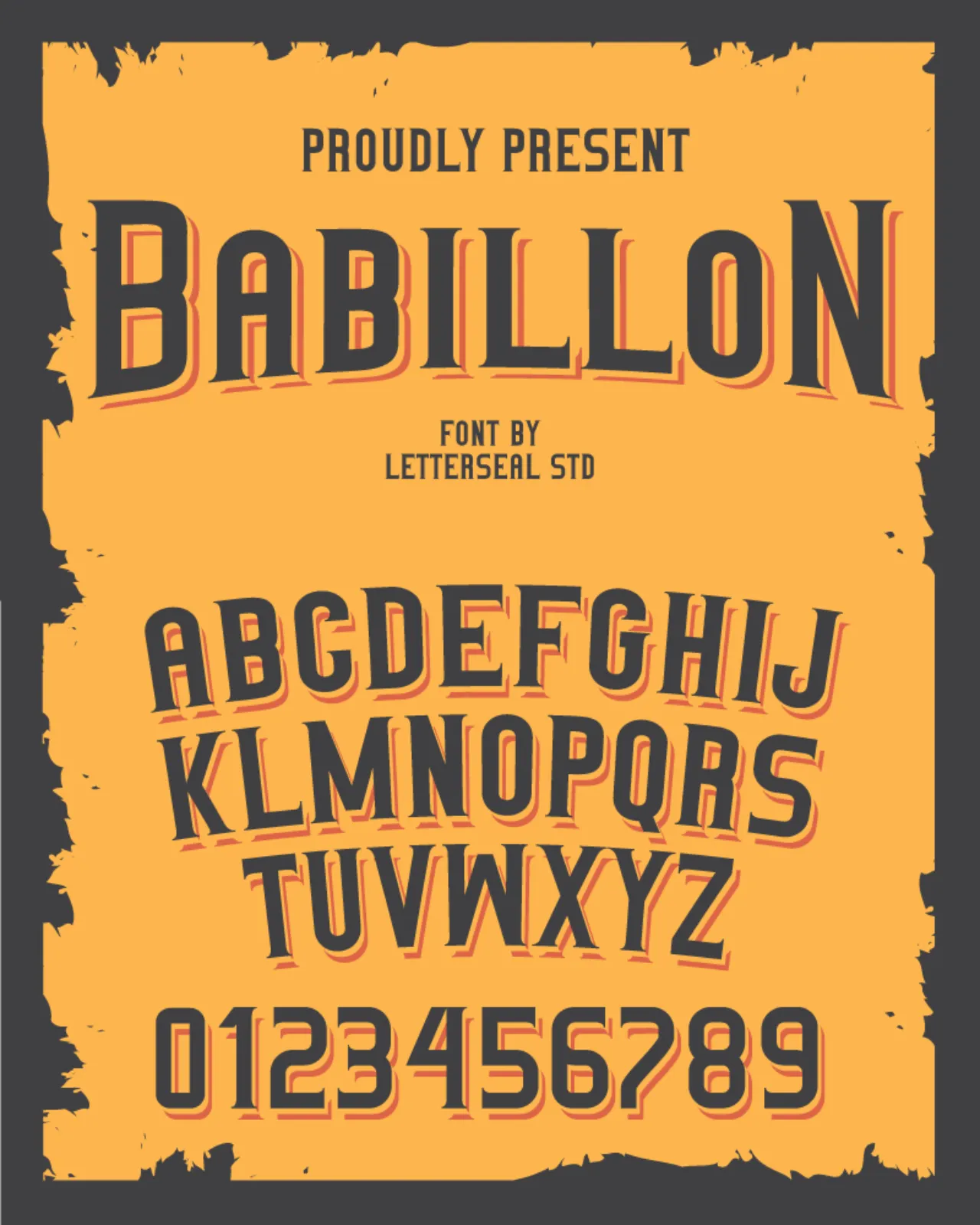
Dari kelompok font serif yang cocok untuk poster ada Babillon. Font yang memiliki desain tebal dan punya sedikit sisi setiap sudutnya membuat font ini terlihat keren.
Terutama untuk poster untuk event tertentu, misalkan seperti musik, acara sekolah, kuliah dan lainnya.
Namun font ini tidak memiliki desain untuk huruf kecil, melainkan huruf besar dan angka saja.
3. Atlane Font
Kemudian untuk poster event karya seni rupa, Atlane font bisa menjadi pilihan kamu. Alasannya karena font ini memiliki coretan di beberapa karakter sehingga terlihat aesthetic.
Selain untuk membuat poster, font ini juga cocok dipakai untuk membuat logo ataupun watermark.
4. BATIK WORLDWIDE Font
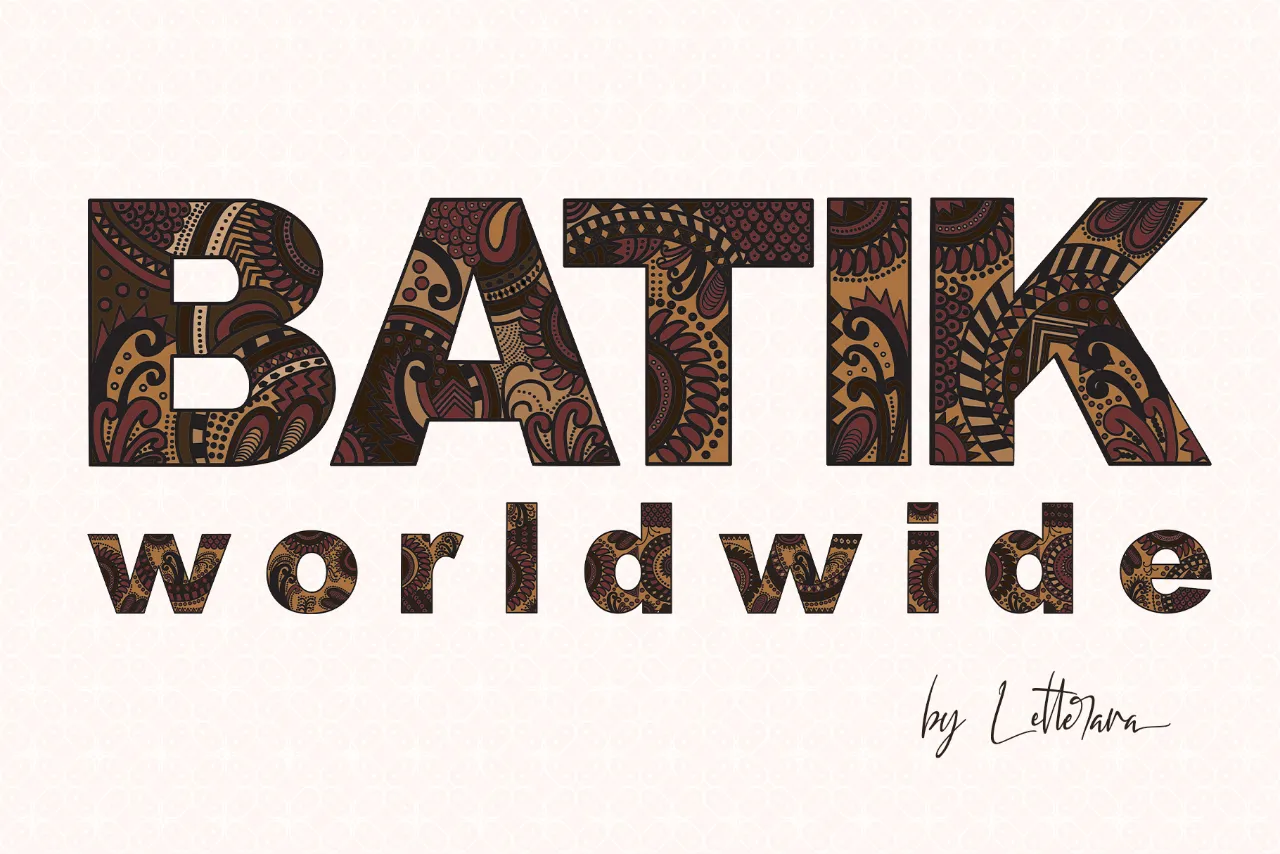
Lanjut lagi ada BATIK WORLDWIDE font yang cocok untuk pembuatan poster bertema Indonesia.
Font asal Indonesia ini didesain khusus dengan fill batik. Sehingga terkesan unik dan kental akan budaya Indonesia.
5. Ombudsman Alternate
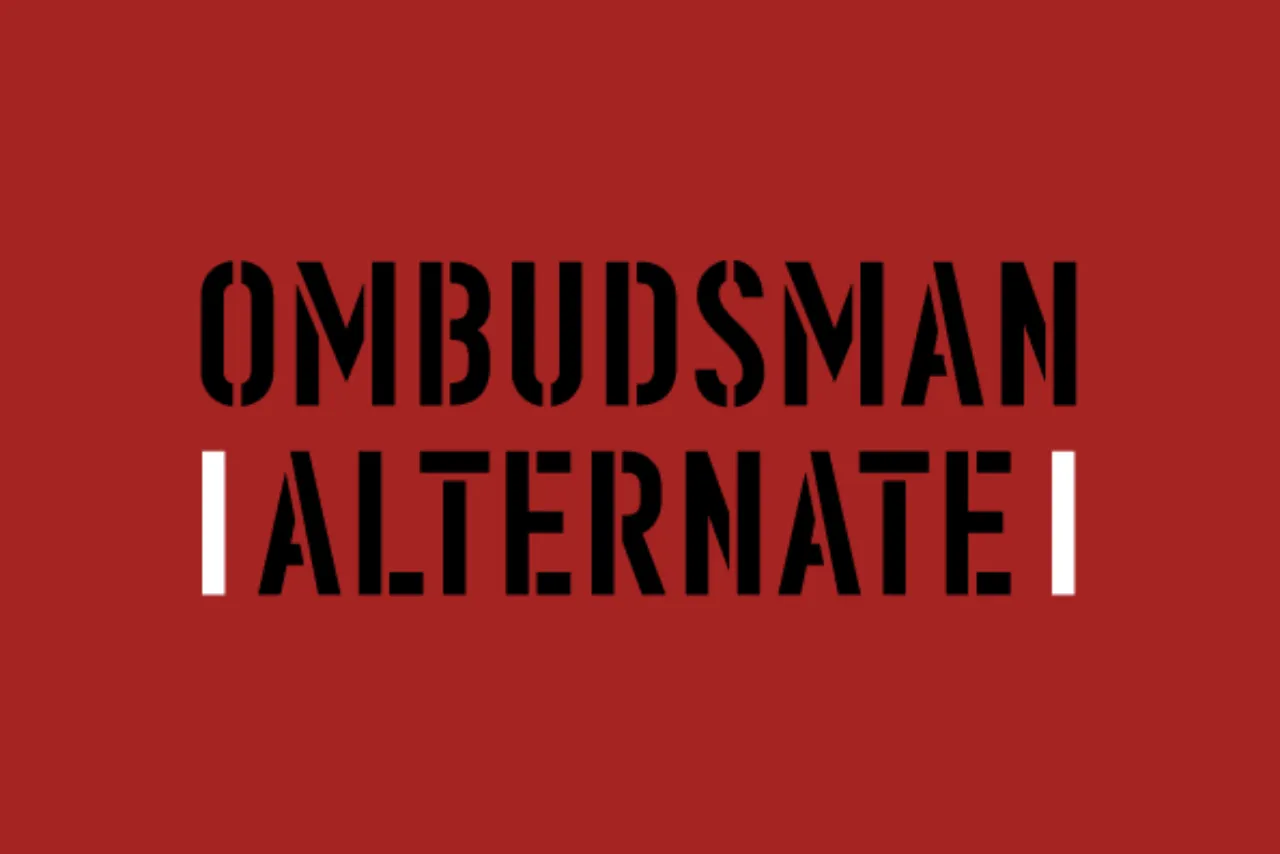
Kalau kamu ingin mencari font poster unik lainnya, kamu bisa pakai Ombudsman Alternate. Font yang memiliki goresan di setiap karakternya ini juga sangat cocok untuk pembuatan poster.
Utamanya poster yang berkaitan dengan jurnalis, hukum dan sejenisnya. Menariknya, font ini terdiri dari 158 karakter yang terdiri dari huruf besar, angka dan simbol khusus.
6. Hamble Font
Kalau kamu mencari font tipografi, Hamble adalah salah satu yang kami rekomendasikan.
Memiliki desain yang bervariasi dan dekoratif di setiap karakter membuat font ini terlihat sangat menarik. Apalagi kalau dipakai untuk event karya seni, class meeting dan lainnya.
7. Blindshot Font
Kemudian untuk font dengan desain brush kamu bisa pakai Blindshot. Font ini memiliki desain yang terkesan liar, sehingga cocok untuk pembuatan poster musik rock atau hardcore.
Selain itu, font ini juga terdiri dari 136 karakter yang terdiri dari simbol khusus, angka dan huruf besar.
8. Moonshine Font
Moonshine adalah salah satu font cursive yang cocok untuk membuat poster. Font dengan desain fill tidak merata ini sangat terlihat menarik.
Karena terdapat juga desain dekoratif yang ada di setiap karakter dari font tersebut. Selain cocok untuk pembuatan font, biasanya Moonshine juga dipakai untuk membuat sablon baju.
9. The Brilliant Font
Dari font kaligrafi ada The Brilliant font. Font yang memiliki kesan ditulis dengan brush dan didesain kaligrafi ini sangat cocok dipilih untuk pembuatan judul poster.
Terutama untuk event poster seperti class meeting, karya seni dan lainnya. Selain itu font ini juga memiliki 353 karakter yang terdiri dari huruf besar, kecil, angka, simbol khusus dan mathematics operator.
10. Millena Font
Adapun Millena font dari desain handwriting dan modern kaligrafi. Font ini juga memiliki sisi keunikan tersendiri, karena terdapat simbol hati di beberapa karakternya.
Karena hal ini, membuat Millena font sangat cocok dipakai untuk membuat poster event feminim. Misalkan seperti poster pelatihan make up, tanaman, karya seni dan lainnya.
11. Hot Jacket Font
Kalau Millena font khusus untuk event poster feminim, maka Hot Jacket ini didesain khusus untuk acara laki-laki. Misalkan seperti musik jass, coffee, kaos distro dan lainnya.
Alasannya karena desain yang ada di font ini memiliki kesan maskulin dengan dekorasi di beberapa karakter.
12. Boldblaster Font
Lalu ada font script Boldblaster yang bisa kamu pakai juga untuk membuat poster. Font ini memakai format bold dan didesain soft supaya terlihat menarik.
Selain itu, font ini juga terbilang memiliki karakter yang sangat lengkap karena terdiri dari 343 karakter. Karakternya seperti huruf besar, huruf kecil, angka, simbol dan karakter khusus.
13. Predator Movie Font
Font Predator Movie. Font ini sangat cocok untuk pembuatan poster film, atau event berkaitan dengan IT.
Dari desain, font ini cocok dipakai untuk membuat judul poster saja. Sedangkan untuk isi poster, kamu harus mencari font yang tipis.
14. Justice League Font
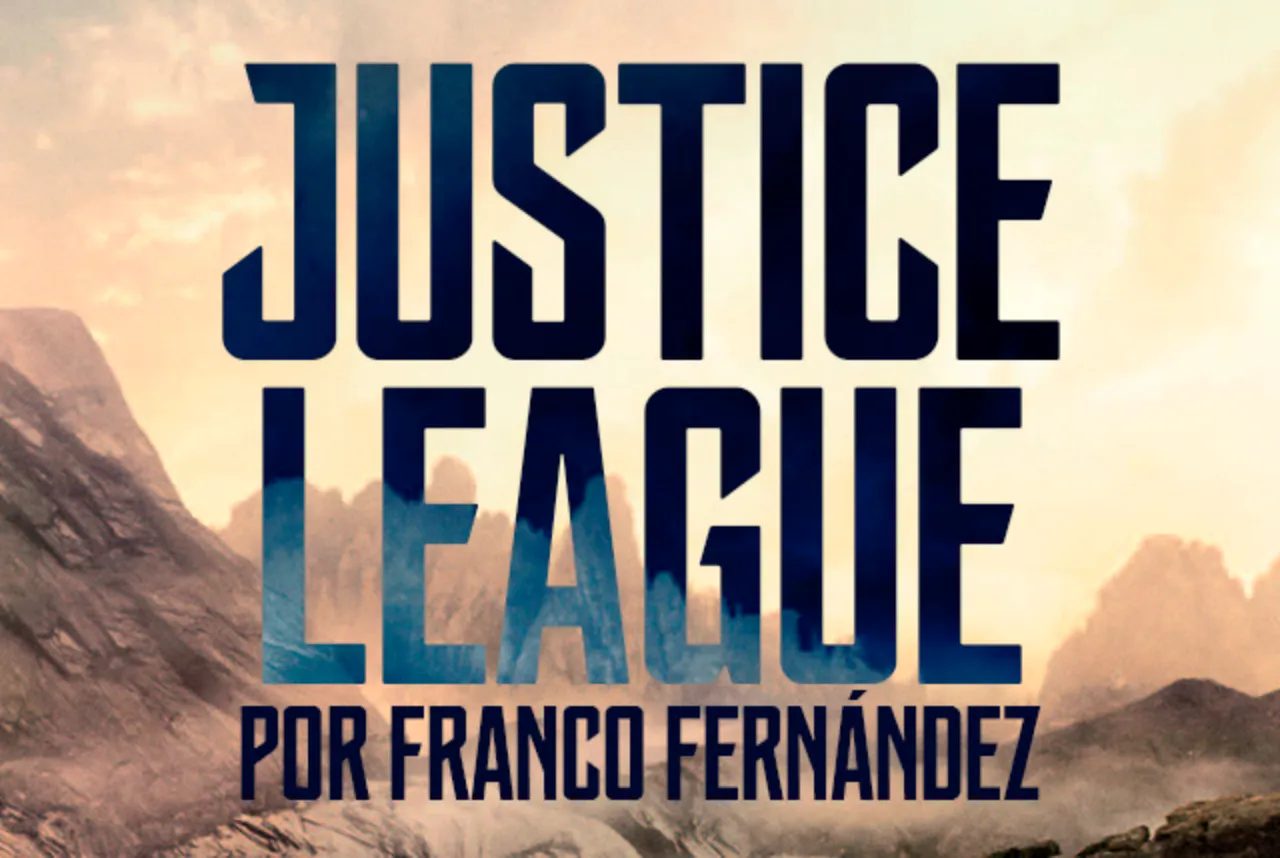
Font ini cocok dan biasa dipakai untuk pembuatan poster film, yaitu Justice League. Biasanya font ini sering digunakan untuk film yang berkaitan dengan superhero.
Selain untuk pembuatan poster film, font ini juga cocok untuk membuat poster yang berkaitan dengan teknologi.
15. Suicide Squad Font
Apa kamu pernah menonton film Suicide Squad? Ya, film yang menggambarkan villain superhero memakai font ini untuk pembuatan poster filmnya.
Oleh karena itu, font ini memiliki sisi keunikan sendiri. Karena terdapat beberapa karakter dengan gambar joker, seperti di huruf A, B, D, O dan lainnya.
16. Shojumaru
Shojumaru adalah salah satu font yang cocok dipakai untuk membuat poster bertemakan jepang.
Alasannya karena font ini sedikit mengambil desain huruf kanji yang dipadukan dengan beberapa sisi unik di setiap karakter.
17. Gravitas One
Kalau kamu ingin memakai font sederhana untuk poster, maka kamu bisa pakai Gravitas One. Font serif modern ini sangat cocok dipakai untuk membuat poster event apapun.
Selain itu, font ini juga terdiri dari 240 glyphs yang terdiri dari huruf besar, kecil, angka dan sebagainya.
18. Ubuntu Titling
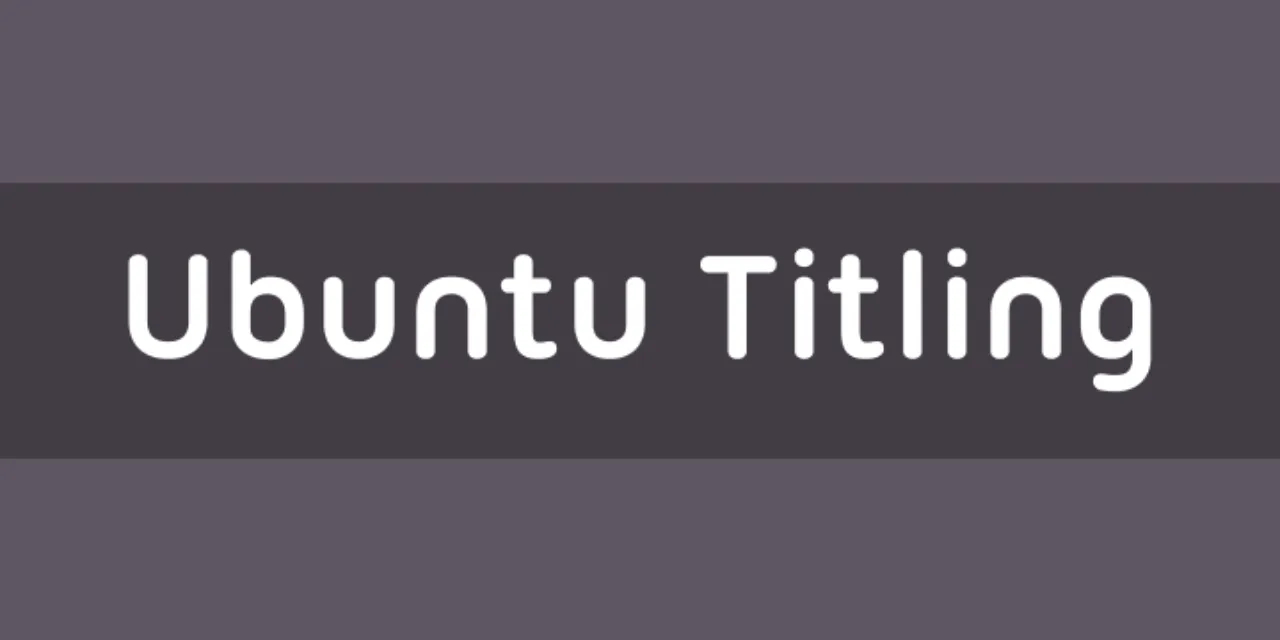
Bagi kamu yang memakai sistem operasi Linux Ubuntu, font ini sangat cocok dipilih. Karena font ini memiliki bentuk layaknya logo Ubuntu itu sendiri.
Karena hal tersebut, membuat font Ubuntu Titling ini cocok dipakai untuk pembuatan poster event teknologi.
19. Ostrich Sans Inline
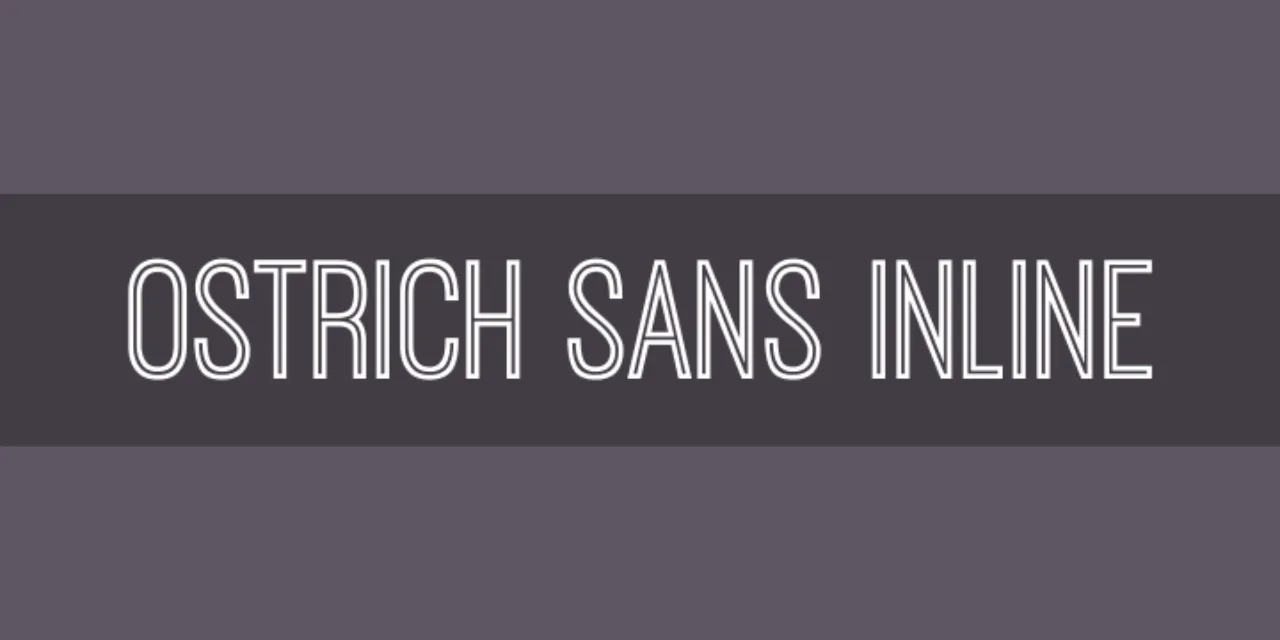
Kemudian kalau kamu ingin memakai font tanpa fill, maka bisa pakai Ostrich Sans Inline. Font ini tersedia 2 jenis, yaitu dengan format regular dan italic.
Menariknya, font ini juga cocok untuk membuat poster event apapun. Karena memiliki desain sederhana, hanya tidak memiliki fill saja.
20. Trade Winds
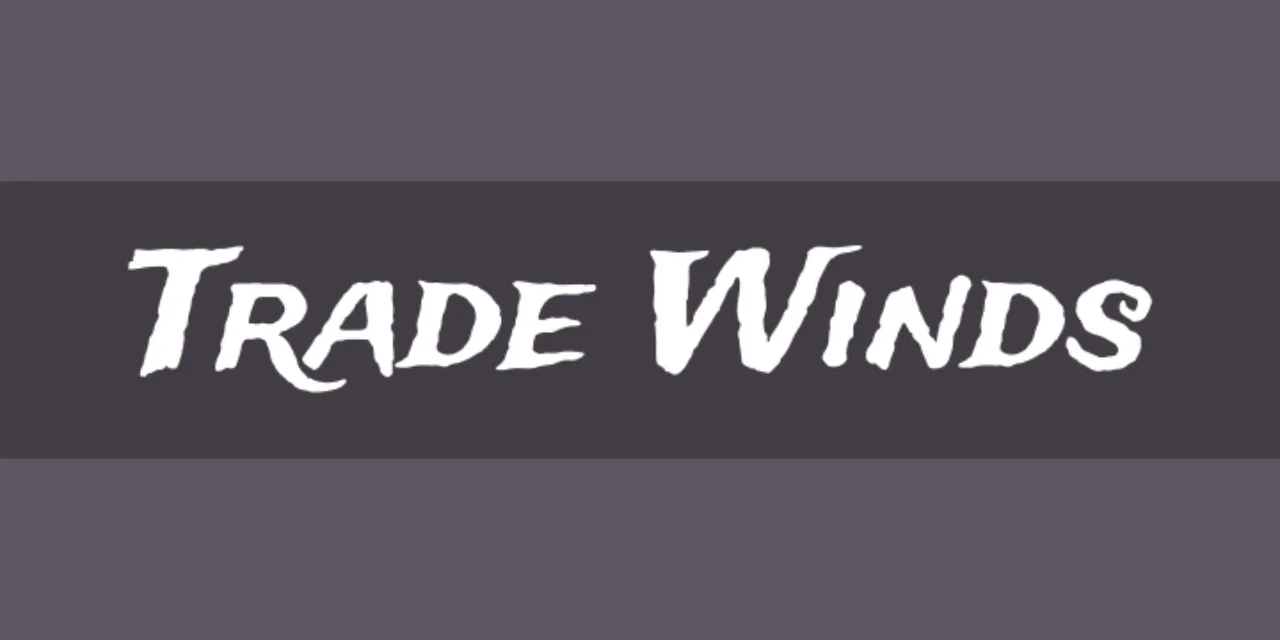
Font yang direkomendasikan untuk membuat poster lainnya adalah Trade Winds. Font dengan desain rough ini sangat cocok dipilih untuk membuat poster tertentu.
Misalkan seperti poster musik, kaos pria dan lainnya. Selain itu, desain di font Trade Winds ini juga cocok dipakai untuk membuat mockup sablon baju.
21. Hardcore Poster
Sedangkan ada Hardcore Poster font yang didesain khusus untuk event musik genre hardcore atau rock.
Biasanya font ini dipakai untuk membuat judul font karena hanya menyediakan karakter huruf besar dan angka saja.
22. Carnage Movie Poster
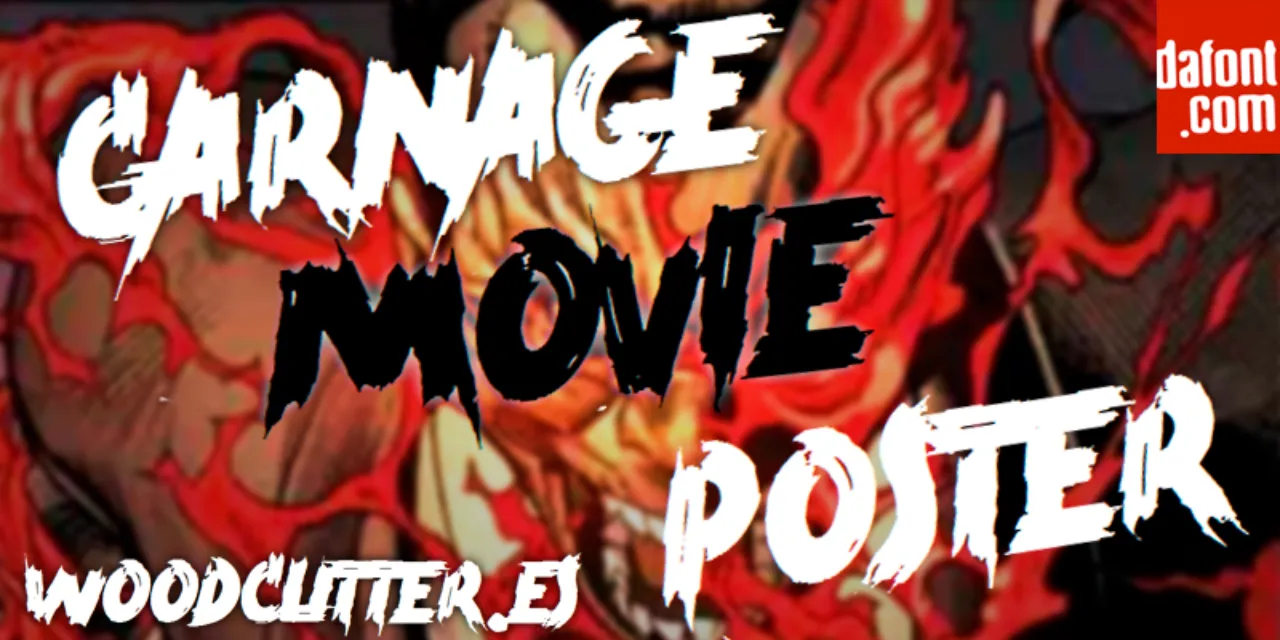
Kalau Carnage Movie Poster bisa kamu pakai untuk membuat poster bertemakan horror. Entah itu film, event rumah hantu atau sebagainya.
Alasannya karena font ini didesain khusus dengan efek brush namun terlihat sedikit keras.
23. Skeleton Type One
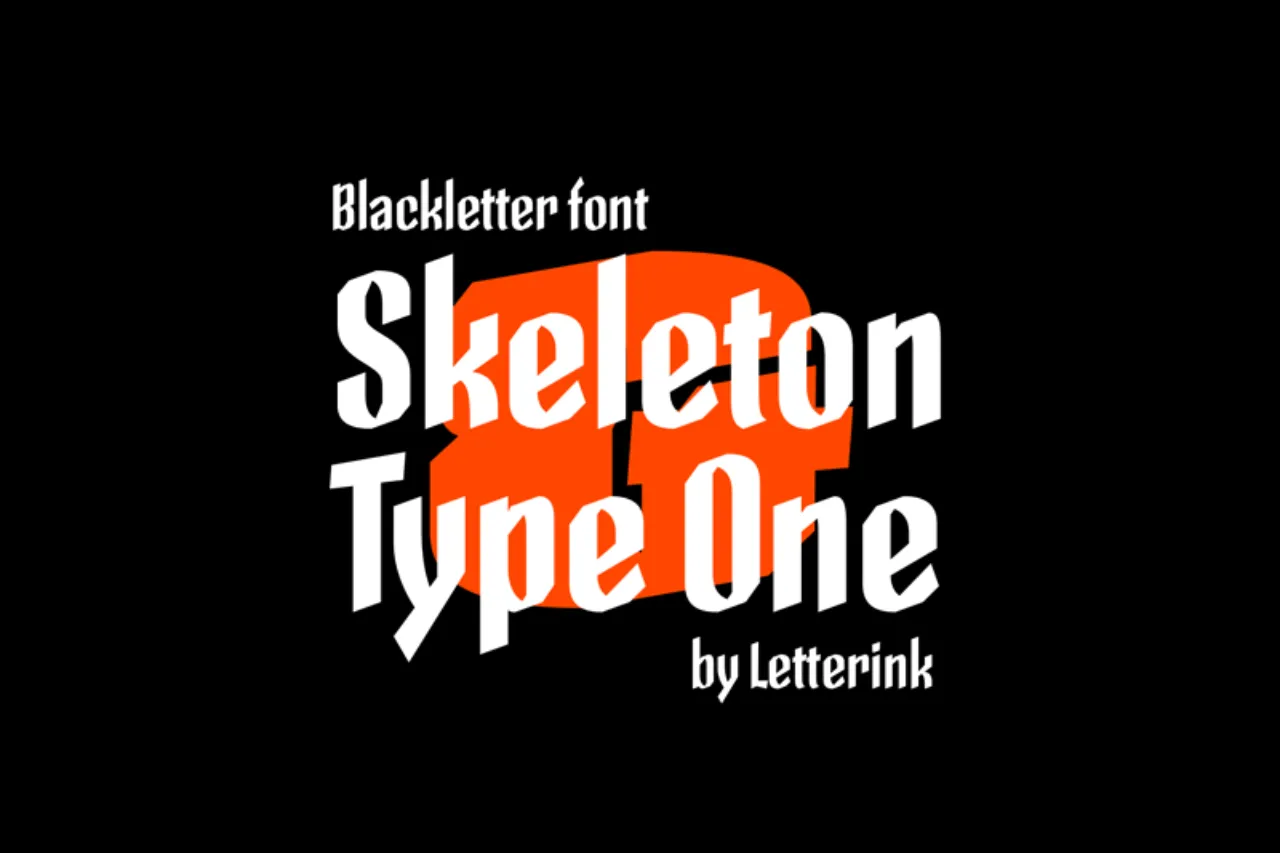
Memiliki desain simple dan cocok dipadukan dengan poster bertemakan casual, membuat font ini banyak yang mengunduhnya.
Alasan lainnya juga terdapat di kelengkapan karakter. Karena font ini dilengkapi karakter huruf besar, kecil, angka dan simbol khusus.
24. GoGo Poster 2020 Font
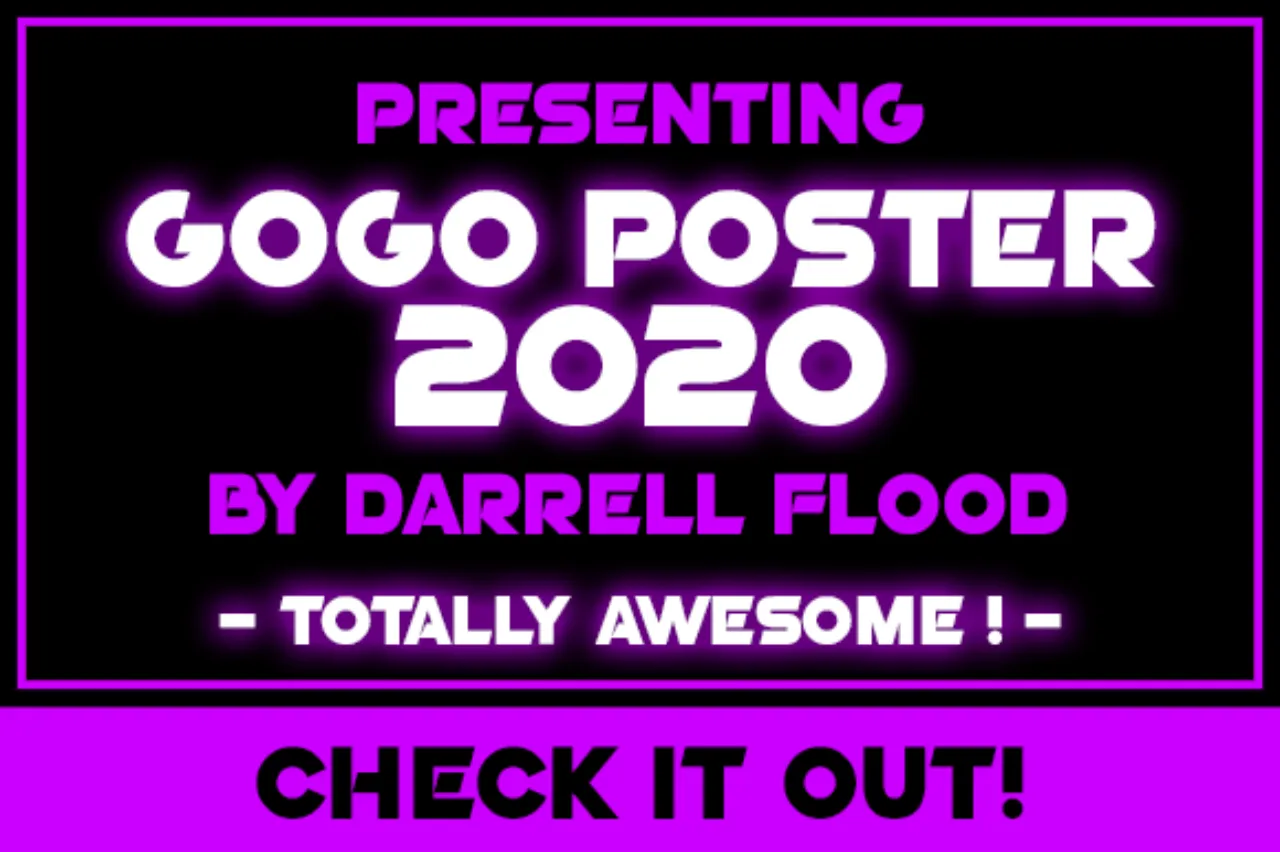
GoGo Poster 2020 adalah font yang cocok dipakai untuk membuat poster bertemakan teknologi. Dengan memakai font ini, kamu bisa padukan dengan efek glow.
Sehingga desain poster yang kamu buat akan terlihat aesthetic.
25. The Poster King
Font The Poster King memiliki ciri khas tertentu karena terdapat beberapa coretan di setiap karakternya.
Sehingga membuat font ini cocok dipakai untuk pembuatan poster musik, karya seni dan sebagainya.
26. Gunplay Font Family
Gunplay font family adalah salah satu jenis sans serif yang direkomendasikan. Utamanya untuk pembuatan poster yang berkaitan dengan olahraga, militer, industri hingga mekanik.
Selain itu, font ini juga memiliki 2 jenis yang berbeda, yaitu regular dan 3D-Regular dengan efek shadow di setiap karakter.
27. Beyond Wonderland Font
Sedangkan kalau kamu ingin membuat poster dengan tema fantasi, karya seni, film dan lainnya, maka kamu bisa download font Beyond Wonderland Font.
Selain cocok dipakai untuk membuat poster, font ini juga bisa kamu pakai untuk desain tattoo atau kartu ucapan.
28. Pricedown Font
Bagi kamu yang suka bermain game lawas, mungkin tidak asing dengan desain font di atas. Ya, font dari game Grand Theft Auto ini bisa juga dipakai untuk membuat poster.
Utamanya poster bertema game, olahraga, sci-fi dan teknologi. Menariknya font ini memiliki 1079 karakter mulai dari huruf besar, kecil, angka, simbol khusus dan karakter unik lainnya.
29. Alba Font Family
Alba font family adalah salah satu font yang sangat fleksibel untuk keperluan desain poster. Alasannya karena font ini memiliki desain sederhana tanpa sisi layaknya huruf pada umumnya.
Selain itu kalau kamu mengunduh font ini akan mendapatkan 3 jenis Alba font. Seperti Alba regular, Alba matter dan Alba super.
30. Casper Font
Terakhir kamu bisa pakai Casper font. Secara spesifik, font ini memiliki desain horror sehingga sangat cocok dipakai untuk event poster tertentu.
Misalkan seperti acara rumah hantu, halloween, film horror dan sebagainya.
Itulah 30 daftar rekomendasi font untuk poster yang kamu pakai. Silahkan pilih font tergantung event poster yang akan kamu buat.